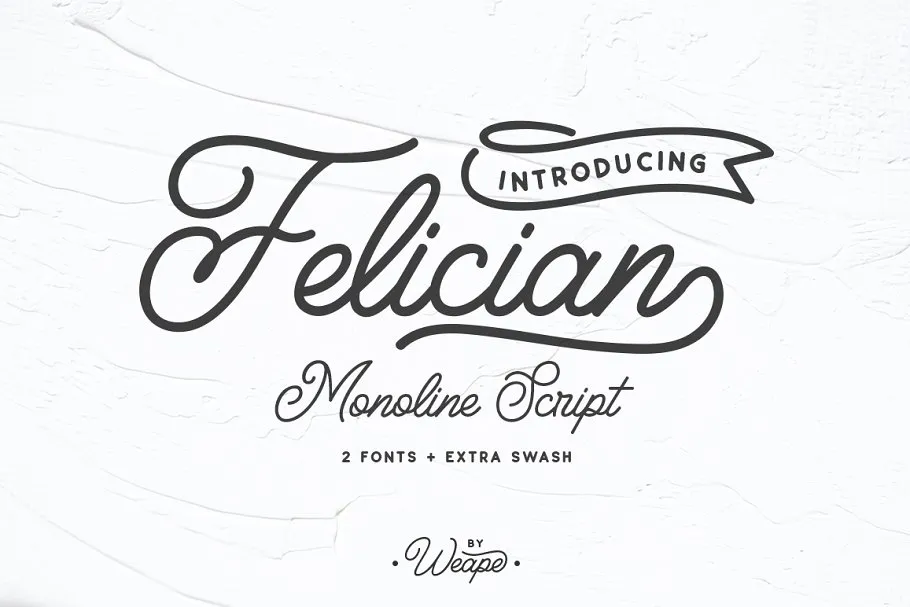
Felician Script Font – Fonte Grátis
Felician Script Font
A fonte Felician Script é uma escolha perfeita para aqueles que buscam um visual elegante e sofisticado em suas criações digitais. Inspirada na tipografia feminina, sensual e glamorosa, ela oferece uma versão moderna de linha simples e muito legível. Desenvolvida pela Weape Design e compartilhada pelo designer 1001fonts, essa fonte traz o melhor da script gráfica com seu estilo monoline, adequado para uma ampla gama de usos, desde logotipos e rótulos até postagens em redes sociais. Possui várias estilos personalizados, ligaduras e ilustrações enroscadas que adicionam ainda mais originalidade a qualquer projeto. Sem dúvidas, é um recurso gráfico que fará sua arte ou marca se destacar no mercado.